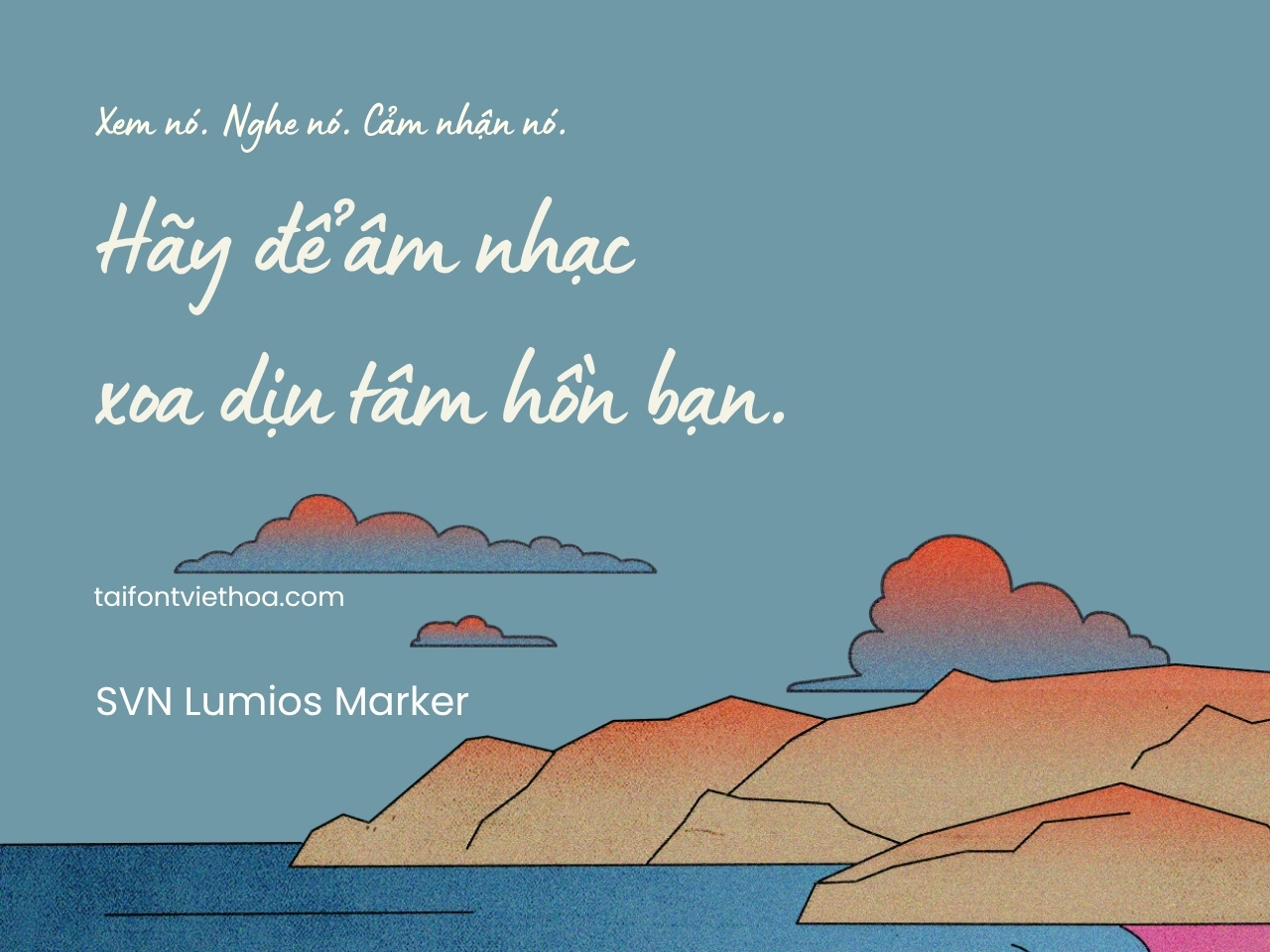
Font việt hóa SVN Lumios Marker
Giới thiệu về font SVN Lumios Marker – Kiểu chữ viết tay phong cách marker trẻ trung và năng động
SVN Lumios Marker là phiên bản Việt hóa của font Lumios Marker – một kiểu chữ handwritten mang phong cách marker với nét chữ đậm, dày và năng động. Font thể hiện sự phóng khoáng, tự nhiên, phù hợp với các dự án thiết kế sáng tạo, quảng cáo, và truyền thông mạng xã hội mang phong cách trẻ trung, cá tính.
Phiên bản Việt hóa của SVN Lumios Marker đã được Taifontviethoa.comchỉnh sửa kỹ lưỡng, hỗ trợ đầy đủ dấu tiếng Việt cùng hơn 60 ngôn ngữ khác. Font giúp các nhà thiết kế dễ dàng ứng dụng trong các sản phẩm đa dạng mà vẫn giữ được phong cách mạnh mẽ, cá tính và linh hoạt.
Thiết kế viết tay mạnh mẽ – Lý tưởng cho thiết kế sáng tạo và truyền thông trẻ
SVN Lumios Marker sở hữu các nét chữ đậm, dày với hiệu ứng marker chân thực, tạo cảm giác tự nhiên và gần gũi. Font có đường nét năng động, phù hợp cho tiêu đề, poster, bài đăng mạng xã hội hoặc các sản phẩm sáng tạo cần sự nổi bật và biểu cảm cá tính.
Ứng dụng lý tưởng: thiết kế poster quảng cáo, bài đăng mạng xã hội, bao bì sản phẩm, logo thương hiệu trẻ trung, thiệp mời và các dự án truyền thông sáng tạo. Ngành nghề phù hợp: truyền thông, quảng cáo, thời trang, giải trí, giáo dục và các thương hiệu định vị theo phong cách năng động, trẻ trung.